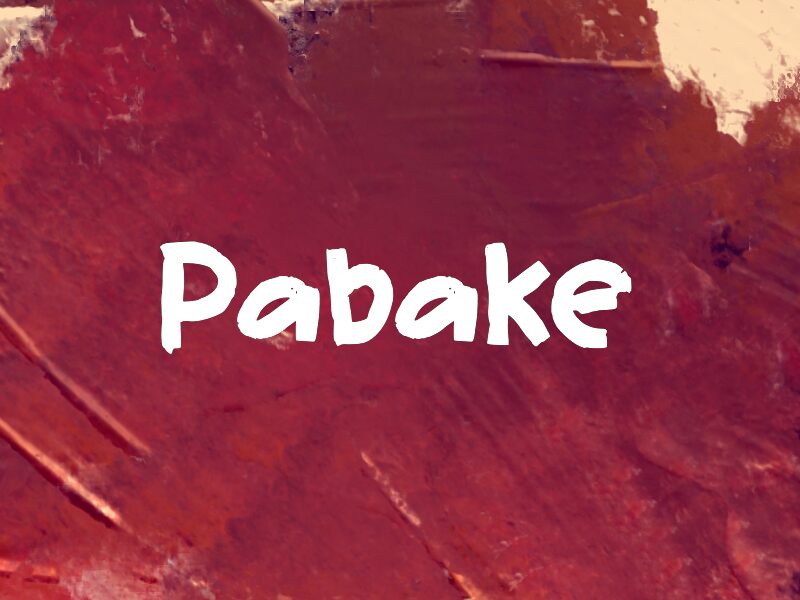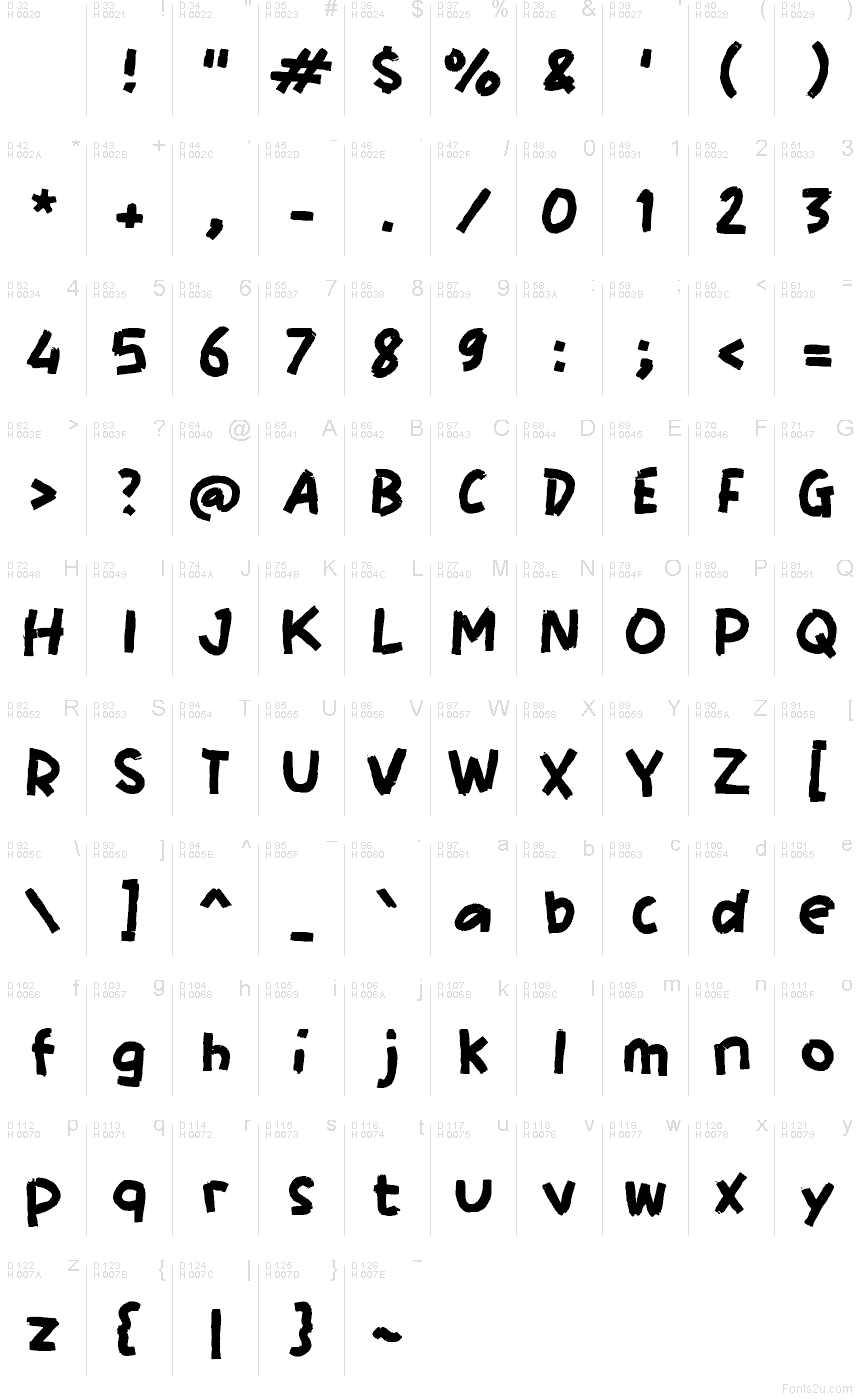
Pabake
Pabake od Wep je bezplatné štetcové písmo charakteristické širokými, zaoblenými ťahmi a suchou, zrnitou textúrou, ktorá je viditeľná na každom znaku. Drsné okraje a mierne nepravidelný rytmus ho približujú k ručne maľovaným nápisom, nie k uhladenej kaligrafii, čo dizajnu dodáva výrazný a uvoľnený charakter.
Táto textúra vynikne na menu v kaviarňach, obaloch produktov, nadpisoch plagátov, náhľadoch na YouTube či letákoch, kde by čistý digitálny štetec pôsobil príliš umelo. Krátke nápisy a etikety produktov ťažia z jeho mäkkej, blokovej siluety, vďaka ktorej pôsobí správa úderne, no stále si zachováva pocit ručnej práce.